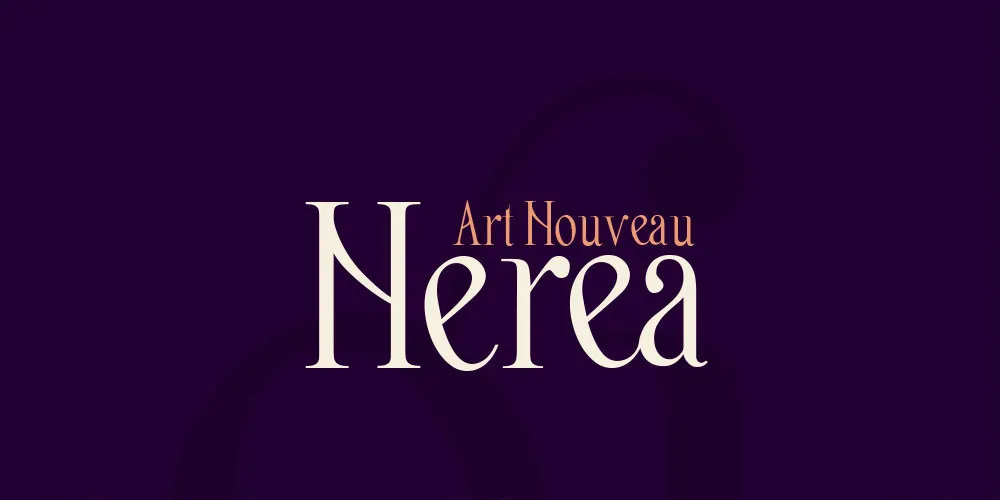
Nerea é uma tipografia Art Nouveau com peso regular que traz uma dose extra de elegância natural. O objetivo do designer Hamilton foi criar uma tipografia rica e verdadeira, inspirada nos arcos sinuosos encontrados na natureza – equilibrando linhas retas fortes contra traços finos e terminações redondas, ou mesmo geométricas. Esses elementos características conferem a Nerea um charme chamativo, especialmente adequado para aplicações em título ou ambientes de grande tipografia. O caráter sensual feminino da fonte é perfeitamente complementada por sua extensa gama de caracteres que apoia várias línguas dos Estados Unidos e Europa. Compre uma licença comercial através de fonts.com, Linotype ou visite o site oficial de Nerea em nerea.lllu.es para obter mais informações.